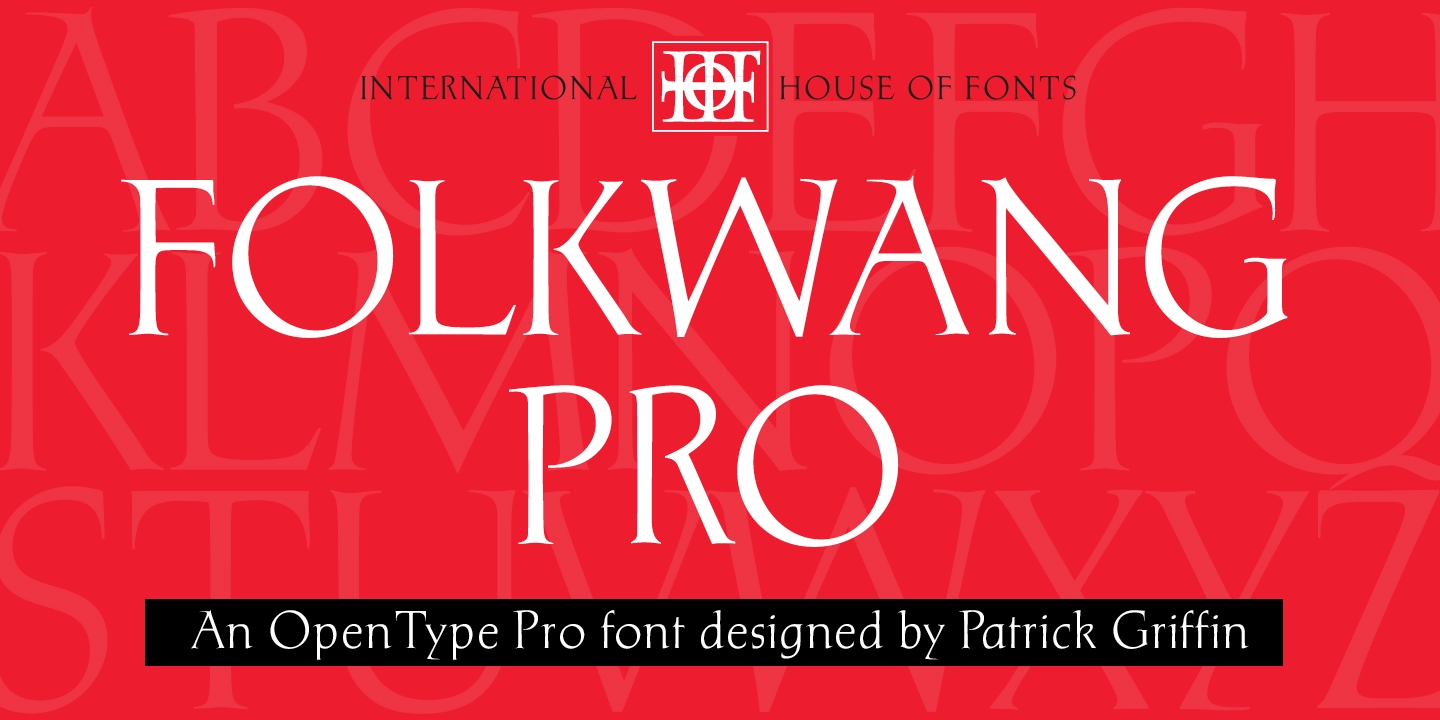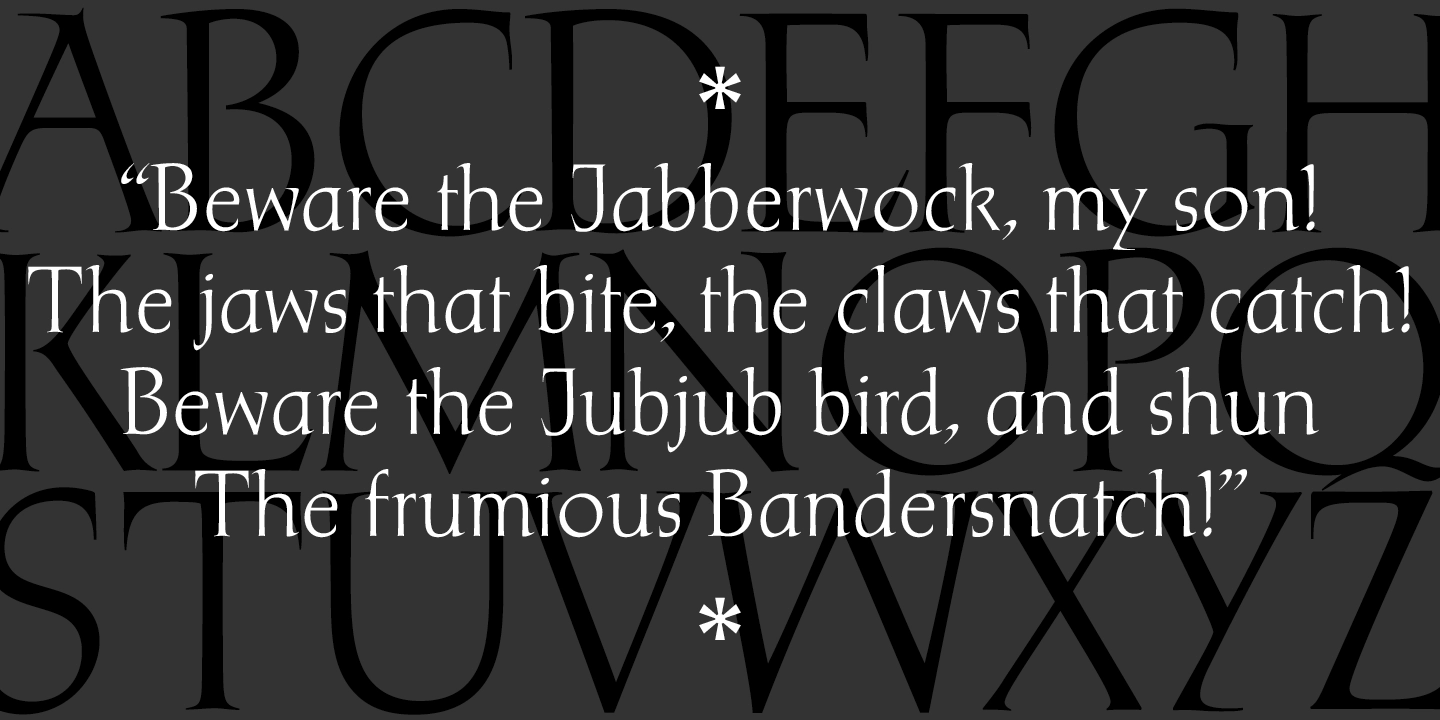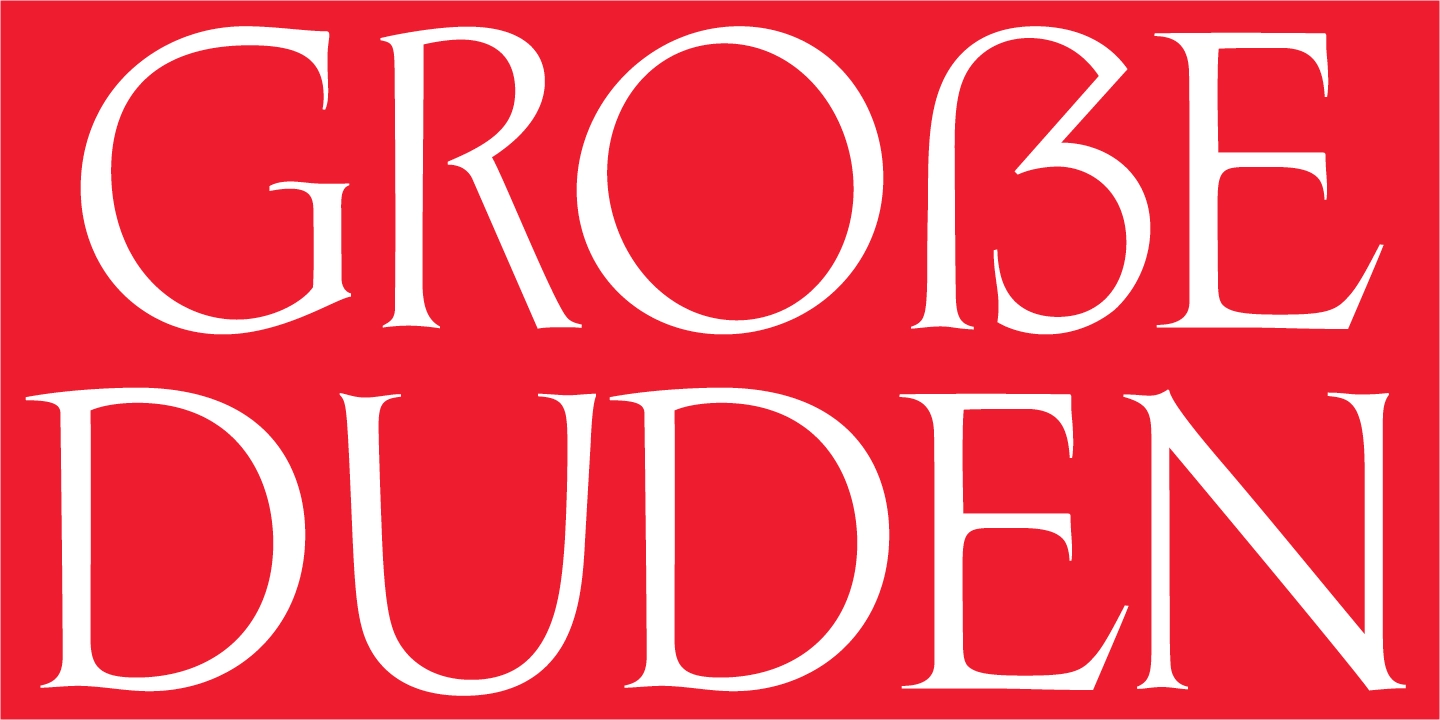
- 1955
- Antiqua humanistisch
Die Folkwang-Schrift von Hermann Schardt wurde Ende der 1940er-Jahre entwickelt, während Schardt die Folkwang Werkkunstschule in Essen leitete. Die Schrift erschien schließlich in den 1950er-Jahren über die Klingspor-Gießerei in drei Schnitten (mager, kursiv, halbfett).
Eine Digitalisierung und Erweiterung gibt es von Patrick Griffin als P22 Folkwang Pro. Es gibt jedoch nur den mageren Schnitt.
Fotosatzmuster von Linotype
Digitale Version von P22